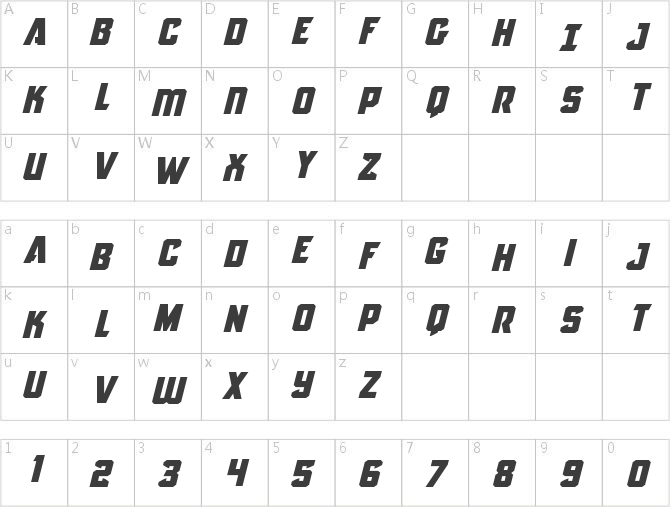
字體名稱: antille
antillesexpandital
antillesexpandital字體字庫(kù)是一款讓人賞心悅目、百看不厭的英文字體,適合各類廣告和產(chǎn)品包裝設(shè)計(jì)應(yīng)用,字體大小0.02MB,格式為ttf字體,上傳用戶是速拓科技,作者/版權(quán)方為未知